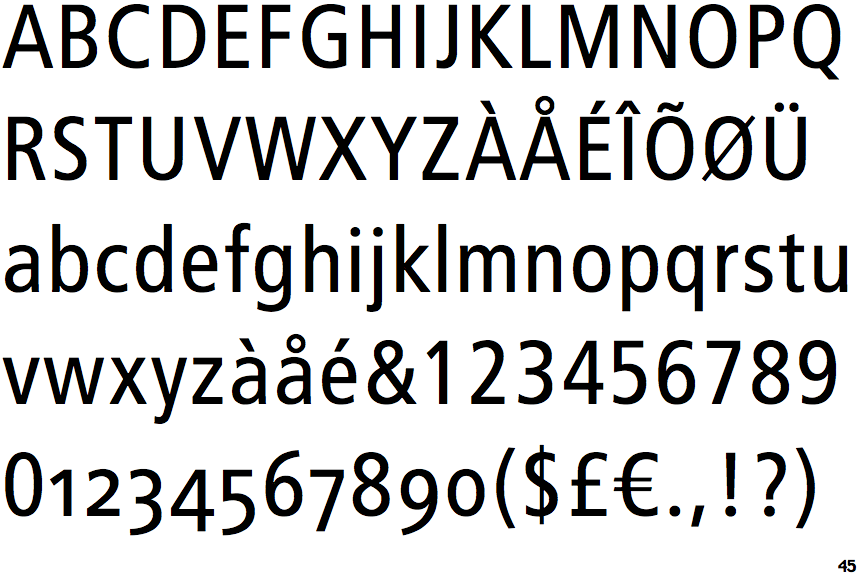
Freie Alternative zur FF Transit?
für meine Bachelor-Arbeit bräuchte ich eigentlich die FF Transit. Es geht um die Neugestaltung der BVG-Beschilderung in Berliner U-Bahnhöfen. Leider kostet der Ganze Spaß und ist auch lizenzrechtlich irgendwie etwas schwierig über die BVG zu besorgen. Ich dürfte eine kostenlose Alternative nehmen, die dieser sehr sehr ähnlich ist. Habt ihr Vorschläge welche da passen könnte? Cool wären ein normaler, ein Bold und ein Italic Schriftschnitt. Bold Italic ist nicht soooo entscheidend.
in meinen Unterlagen steht da was interessantes zur Suche:
Typeface:    FF Transit Print
Designer:    MetaDesign
Year:        1997
Publisher:    FontFont
Influenced by:    Frutiger Condensed
Originally developed for signage in Berlin, and used
in several German cities.
An OpenType font that includes both lining and oldstyle
figures.
Du musst also nach freien Alternativen zur Frutiger mit schmalen Schnitten suchen. Und dann wird es in meine Augen sehr viel einfacher mit der Suche. *hüstel* Da finde ich in meinem E-Katalog unter Grotesk/Humanist einiges:
Vegur; License: Free for personal use; Date added: Jan 17 2014:
Dann gibt es die OPTI Franz in Regular und Bold frei für die nichtkommerzielle Nutzung unter:
Ein Blick auf die ähnliche Schriften zur FF Transit kann da auch Ergebnisse bringen:
Beim Schriftenhörnchen habe ich Sans + [Humanist|Condensed] ausprobiert, war dabei aber sehr erfolglos. Es gibt sogar unter Humanist den Tag Frutiger, aber der führt in die Irre zu einer sehr weit entfernten Schrift Namens Mentone ... Ansonsten kannst Du mal mit dem groben Rechen über das Internet gehen: „Freie Alternativen zur Frutiger“
Viel Spaß und noch mehr Glück bei der Suche, auch wenn ich keine echten Alternativen aufzeigen konnte ...
Unter welchen Bedingungen hat eine Anfrage da Aussicht auf Erfolg? Reicht eine BA/MA/Diplom-Arbeit? Es sollte aber einige Bereiche geben für die so was wenig erfolgreich ist. Virtueller Modellbau und/oder „private“ Dokumente zur Veranschaulichung solcher Sachverhalte dürften da keinen Erfolg bei der Anfrage geben? Falls der OP eine Anfrage stellt wäre der Ausgang und ggf. die Begründung dafür hier auch sehr interessant.
Kleines FAQ: Ich brauch für eine (nicht kommerzielle!) Arbeit einen oder mehrere für mich unbezahlbare Schnitte einer Schrift. Wie gehe ich dabei vor um an diese Schnitte oder ggf. an (freien) Alternativen heranzukommen?
PS: Die Humanist 777 von Bitstream ist auch eine Frutiger, aber sie hat leider keine schmalen Schnitte. Sie ist durch die Verteilung der Bitstream-Schriften mit den vielen Corel-Produkten wie Corel-Draw sehr gut verfügbar, teilweise sogar über geschenkte OEW-Corel-Draw umsonst und trotzdem halbwegs legal zu beziehen. So urteilten zumindest deutsche Gerichte noch vor einiger Zeit ... über den Verkauf von OEM-Software. Örgh ... Juristen ... Auf hoher See und vor Gericht ... Jaja ...